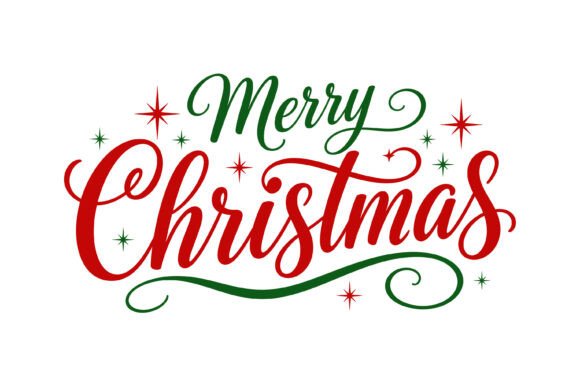
Merry Christmas Script Typography
適切なデザイン要素を見つけるのは難しい場合がありますが、Merry Christmas Script Typographyは作品を即座に引き立てる優れたコレクションを提供します。
POD(オンデマンド印刷)製品、結婚式の招待状、またはソーシャルメディアのグラフィックを作成している場合でも、Merry Christmas Script Typographyは理想的です。